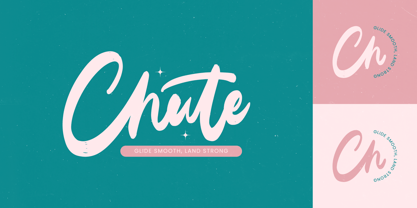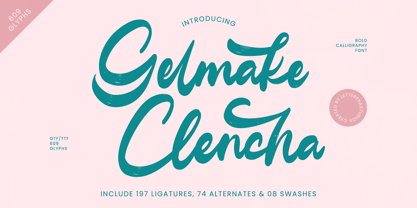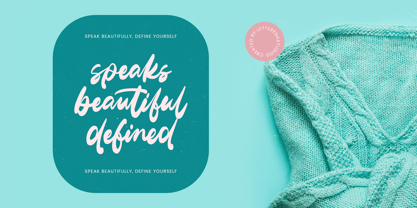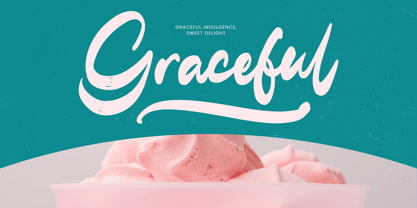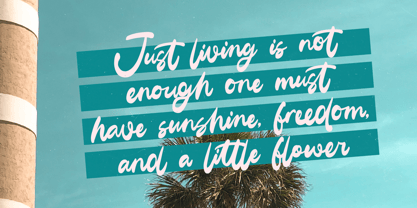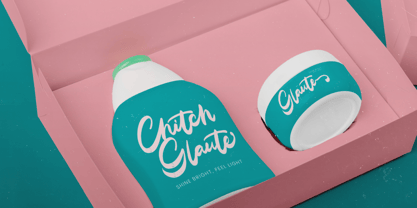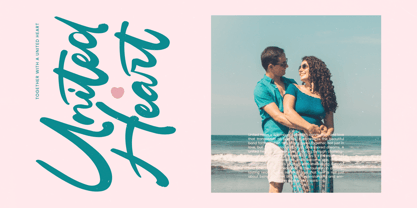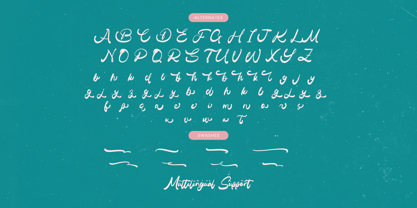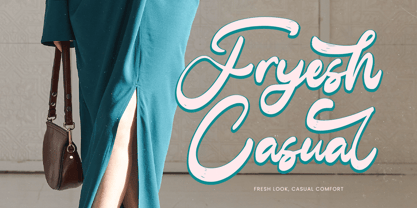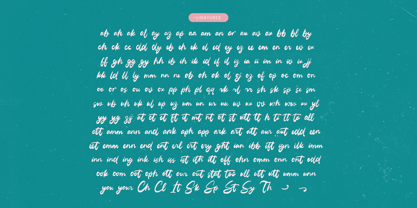
Gelmake Clencha
La familia tipográfica Gelmake Clencha fue diseñada por Heru Utama Putra y publicada por Letterena Studios. Gelmake Clencha contiene 2 estilos y opciones de paquete familiar.
Gelmake Clencha - Bold Calligraphy Font , from Letterena, is a Luxury Script font, suitable for any projects such as: logos, branding projects, homeware designs, product packaging, mugs, quotes, posters, shopping bags, t-shirts, book covers, name card, invitation cards, greeting cards, label, photography, watermark, special events, and all your other luxury and beautiful projects that need a Luxury Script taste.